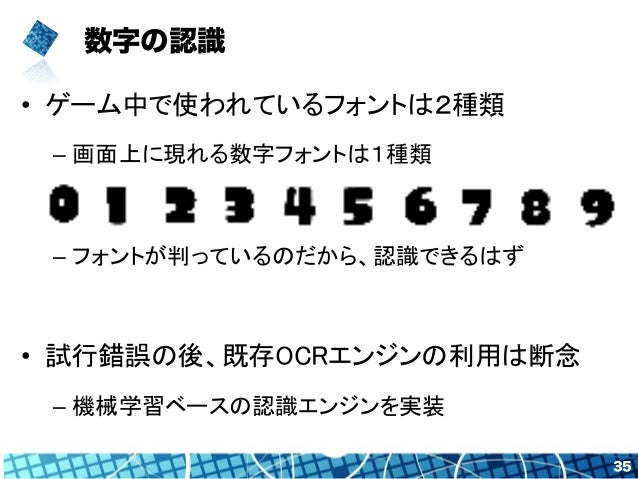
スプラトゥーン 文字 フォント
スプラトゥーン 文字 フォント. ゲーム内のフォント(文字の形)を再現したttfファイルが配布される! イカ語も非常に独特ですが、スプラトゥーンは ゲーム内のフォント(文字の形)も非常に独特です。 敵にやられた時に表示される、↓なんかはインパクトがありますよね。. Splatoon風フォント と漢字について Splatoon でイカしたフリーフォントというのがあるようです。 しかし、これ 3つのフォントを合わせてます。. スプラトゥーンで使われているフォントとは? 人気ゲーム「Splatoon(スプラトゥーン)」で使用されている(であろう)フォントは、こちらの記事 でアテが付けられています。 どうもゲームとウェブサイトで使われているフォントが違うみたい。.
- 任天堂Wii Uの人気ゲームソフト「スプラトゥーン」では、ゲーム内に一見解読不能な象形文字っぽいフォント(通称「イカ文字」)が登場しますが、イカ文字以外にもステージ情報やニュースなどの表示には独特のフォントが使われています。そんなスプラトゥーン内で使われている. 文字 文字色 画像を保存 フォントはあらむぎ様のイカモドキを使わせて頂いてます。あらむぎ様のイカモドキを使わせて. さてどうしたものか。スプラトゥーンフォントを学習させるか — あつし🌘人生クリア率10.1% (@Anaakikutsushit) 18年12月28日.
なまえをいれてください (ワッチョイ 9135-Jc3G) (月) 21:22:.74 ID:ZBga4i/q0 >>938. スプラトゥーン2の公式アプリであるイカリング2にアクセスすると、Web フォントが二つロードされる。78 KBのフォントと 587 KBのフォント。サイズから言って後者のフォントが漢字を含んでいるフォントだろう。. Macintosh対応 CIDフォント G2サンセリフ-U 高解像度版 ちょっと個人ではどうしようもないので似たようなフォントを探そうね イカ文字(象形文字っぽい方)は割愛。 #スプラトゥーン そういえばイカ語で意味が分かってる単語を集めた画像作ったんだった。DL.
記事: スプラトゥーンあの特殊字体(フォント)は非売品?類似フォントの開発・配布情報まとめ - 踊るびあほりっく というわけで早速遊んでいきましょう。 ・Splatoon1のフォント. スプラトゥーンフォント 『スプラトゥーン』は、任天堂開発・販売の Wii U用第三者視点シューティングゲームです。 15年5月にリリースされました。. となるとイカ文字の標準的なフォントが欲しくなります。 ゴシック体 (sans-serif)、そして明朝体 (serif)です。 今回はスプラトゥーン内で使用されている幾つかの文字を抽出し、見つからない文字は適当に作り出し、それっぽくアルファベットに当てはめてみ.